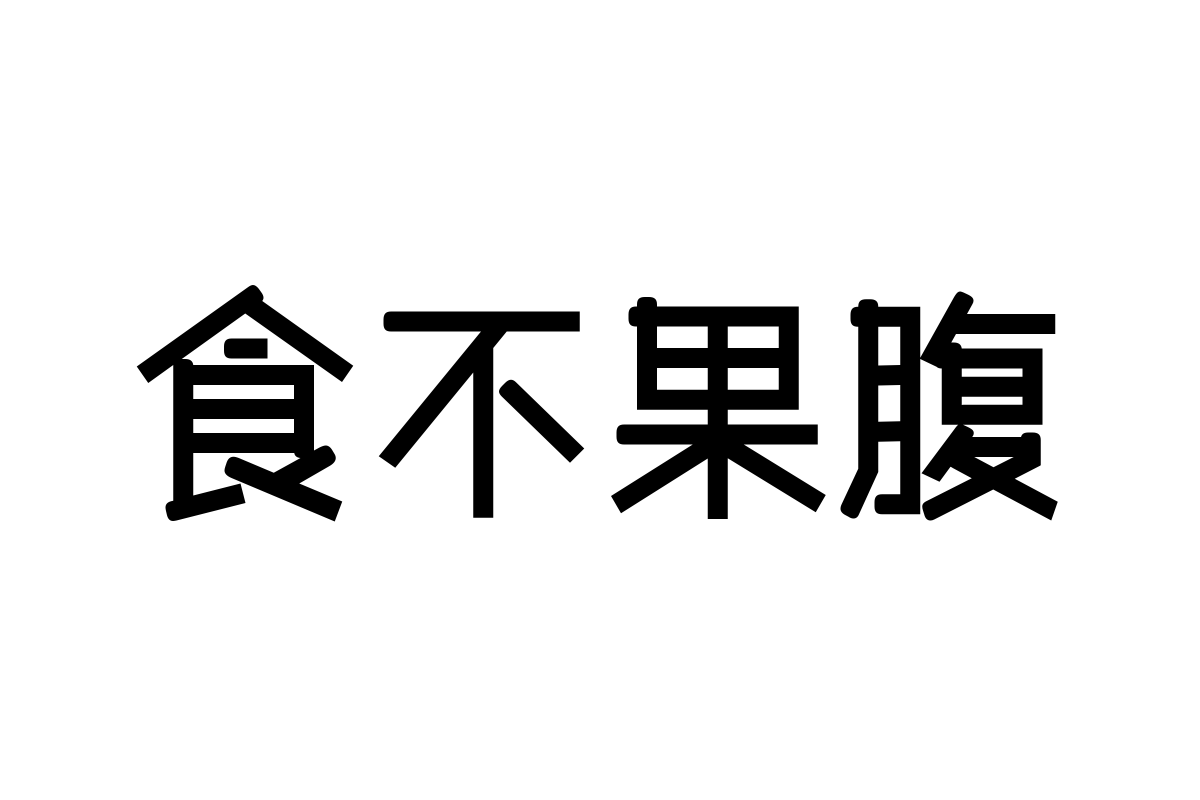
“三极傻黑简体” 是一种特殊的字体,通常用于中文排版。这种字体的特点是字形简洁,笔画清晰,易于阅读。它的设计灵感来源于中国传统的书法艺术,但又不同于传统的楷书、行书或草书。
这种字体的特点是:
1. 字形简洁:每个字的笔画数量相对较少,使得整个字体看起来更加简洁明了。
2. 笔画清晰:每个字的笔画都清晰可辨,没有模糊不清的部分。
3. 易于阅读:由于字形简单,所以阅读起来非常轻松,不需要花费太多时间去理解每个字的含义。
4. 适合快速阅读:在需要快速阅读大量文字的情况下,这种字体可以提供更好的阅读体验。
总的来说,”三极傻黑简体” 是一种非常适合现代快节奏生活和数字化阅读环境的字体。